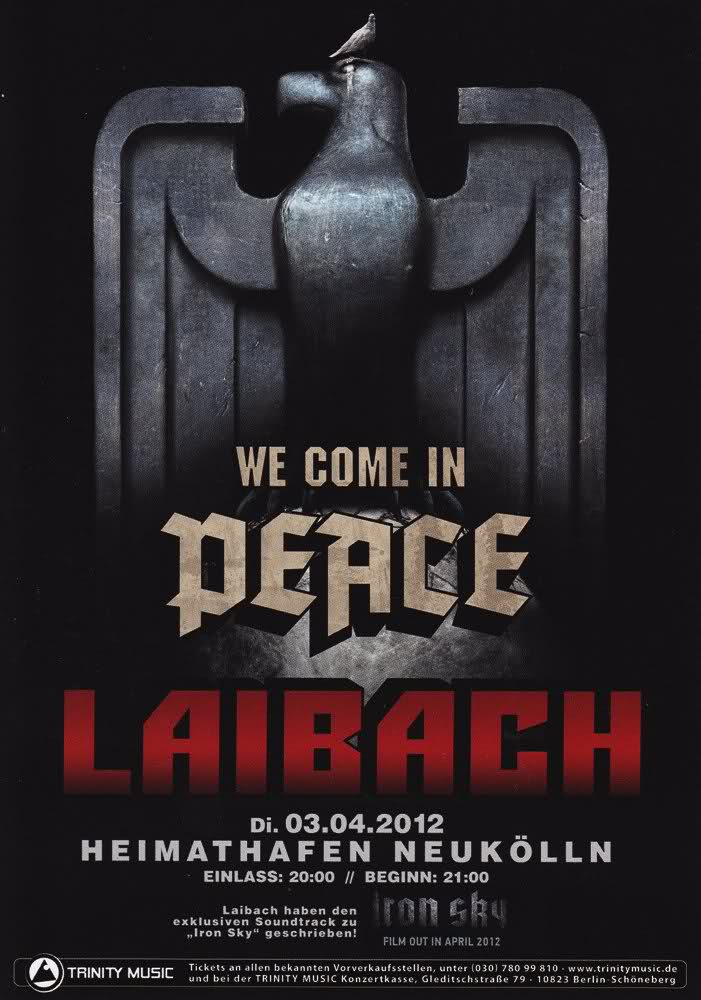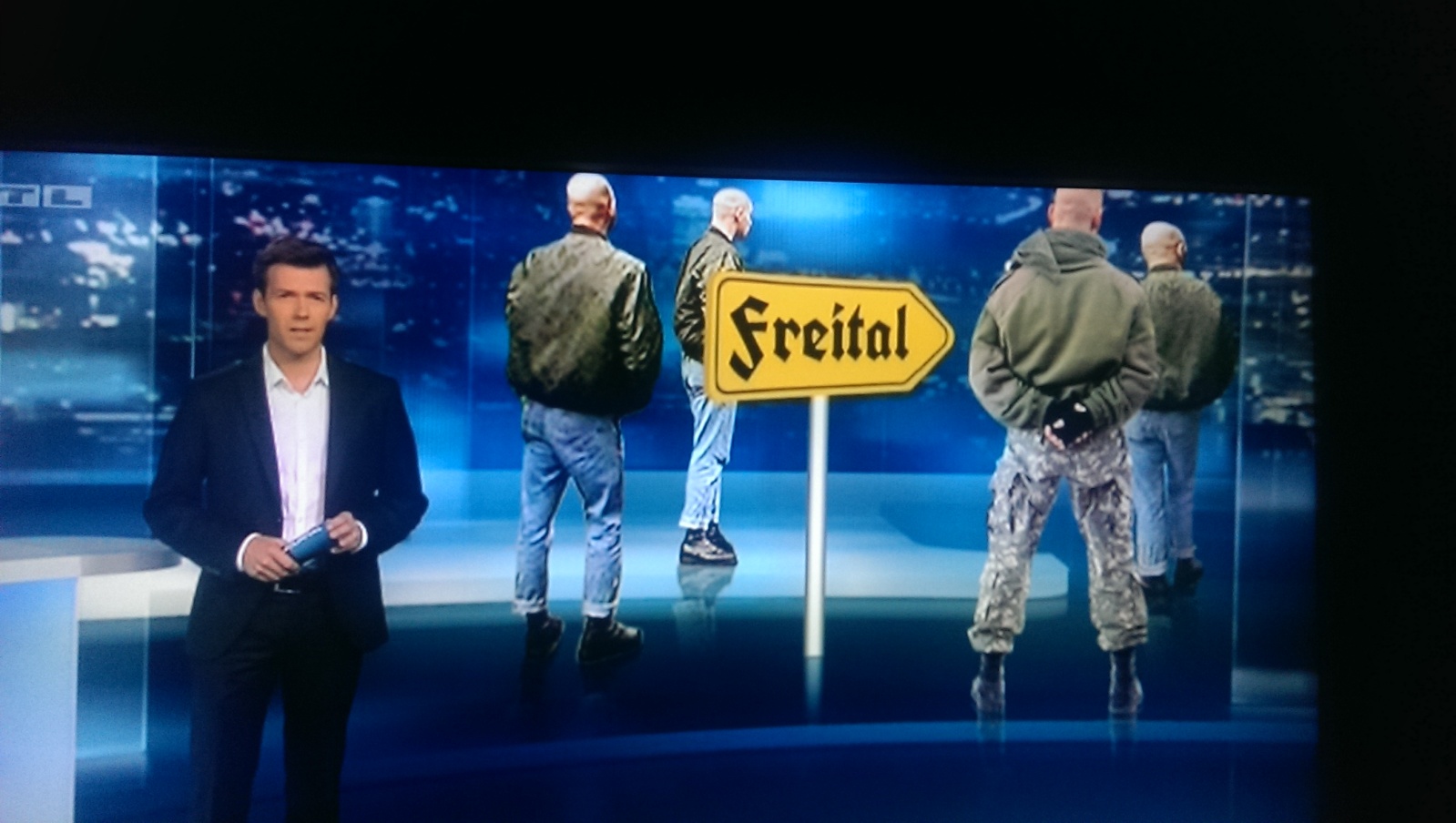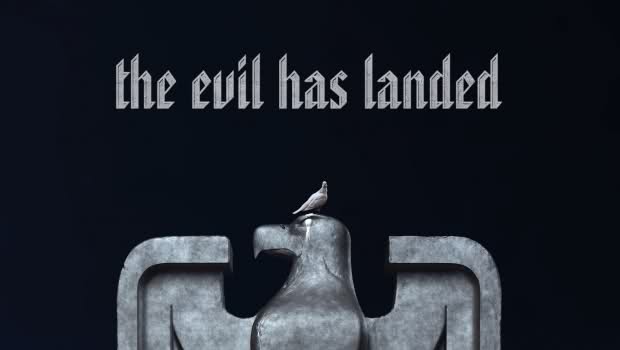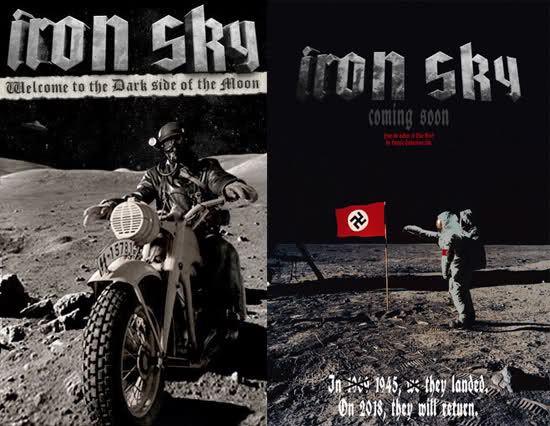
Schaftstiefelgrotesk?
Ich habe mal schnell die Kapitelanfänge aus der Hüfte abgelichtet:
Ja, da haste doch nen ganz repräsentativen Überblick.
Ich möchte noch erwähnen wie toll das Buch zeigt, wie klischeebehaftet die Fraktur ist. Ich dachte das wüsste ich, aber es geht noch viel weiter. Da benutzen Linksradikale noch Gebrochenes, während Ärzte – die sich eigentlich darum kümmern sollten – mit der Futura anbändeln. Quer durch Klassen, Religionen, Nationen, Generationen gehen die Grenzen.
Das Wort "Schaftstiefelgrotesk" taucht doch einmal auf. Auf Englisch heißt es "Jackboot Grotesque".
Ich wäre für die Nennung einiger Schriftnamen sehr dankbar.
Die von mir gezeigten Schriften in der Reihenfolge der Abbildung:
Tannenberg
Deutschland
Element
Deutsch Gotisch (keine original Bleisatz-Vorlage bekannt – oder doch ?)
Potsdam
licht Tannenberg
lichte National
Kurmark
Wieynck-Gotisch
lichte Wieynck-Gotisch
Weiß-Gotisch
Gotenburg
Offenbach
Die Schriften von Georg:
Element
Gotenburg
Tannenberg
National
Im PDF-Schriftmusterprospekt von Gerhard Helzel (http://www.fraktur.biz) gibt es eine ganze Seite mit »gebrochener Gotisch«.
Flosemann
Die Bezeichnung »Schaftstiefelgrotesk« ist übrigens entgegen anderslautender Gerüchte
keine Erfindung des Typografen Hans Peter Willberg. Ich selbst habe als junger Schriftsetzer
Anfang der 1970er Jahre in der Druckerei Limbach (Braunschweig) einen älteren Kollegen
aus Berlin kennengelernt, der diese Schriften genau so bezeichnete.
ich such ja schon seit langem ein beispiel vom einsatz einer
gebrochenen grotesk im ausland, natürlich vor 1945.
endlich hab ich eins gefunden! :biglove:
filmtitel und abspann »Die Seeteufel« von 1924
ja, möglichkeiten gibt es viele: new blackletter, simple blackletter grotesk, new gothics ...
ich wollte nur wissen ob es generell schon ein wort gibt was im englischen sprachraum dafür verwendet wird.